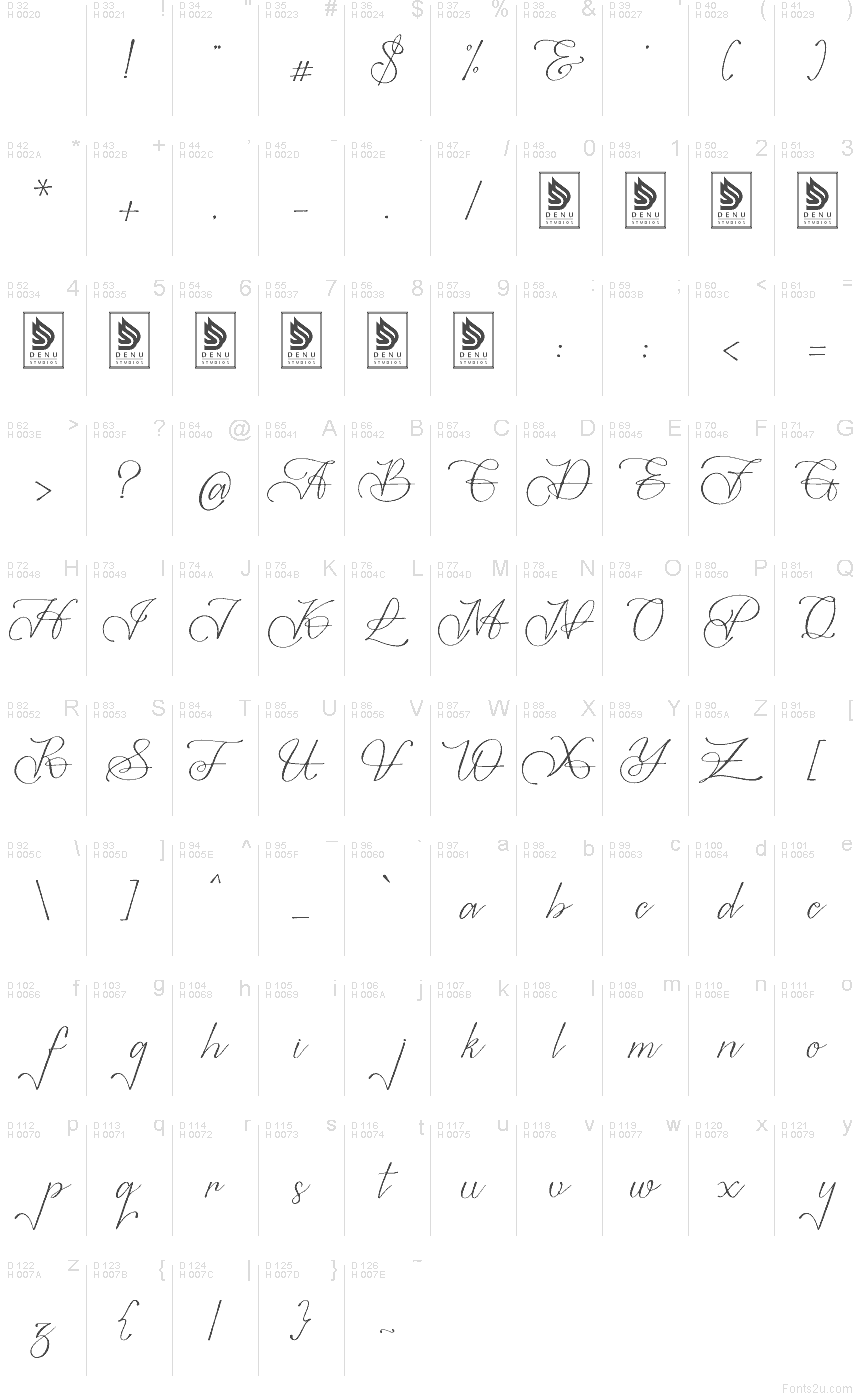
Mangkinoy de Denustudios es una tipografía caligráfica gratuita de trazo ligero y fluido, con largas curvas que otorgan a las letras un aire equilibrado y personal. El estilo resulta elegante en lugar de recargado, con trazos iniciales elevados, conexiones ligeras y algunos adornos generosos que estiran el texto y lo mantienen en movimiento.
Encaja perfectamente en papelería de bodas, branding de belleza, packaging boutique, titulares y tarjetas para redes sociales, donde una voz manuscrita suave es más importante que la formalidad estricta. Como fuente gratuita, Mangkinoy es especialmente útil para logotipos, citas breves e iniciales tipo monograma, ya que esos trazos extendidos y el ritmo delicado necesitan algo de espacio para lucirse.